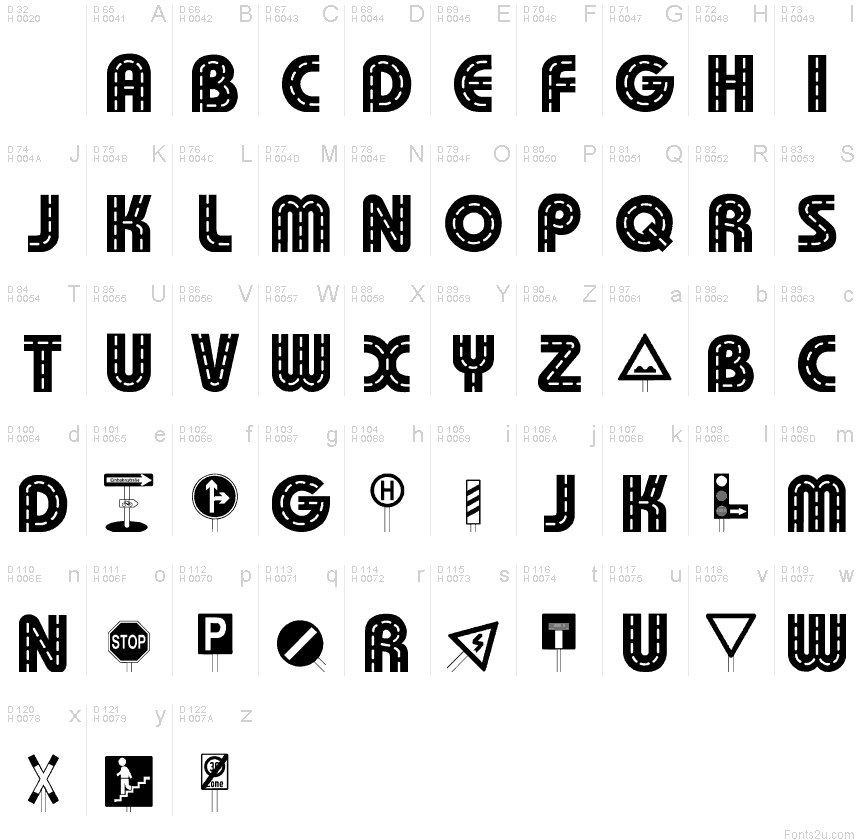
Schilderwald Alt autorstwa Susanne Fiedler to darmowy krój typu display inspirowany oznakowaniem drogowym, o dynamicznym, miejskim charakterze. Litery czerpią z grafiki drogowej i elementów miejskiej infrastruktury – grube czarne kształty, przerywane linie, strzałki, okręgi i pasiaste znaki – dzięki czemu alfabet czyta się bardziej jak zwarty system ikon nawigacyjnych niż zwykły zestaw liter.
Sprawia to, że jest to naturalny wybór do nagłówków plakatów, identyfikacji wizualnych wydarzeń, okładek albumów, plansz tytułowych czy grafik sklepowych, gdzie darmowy font z tak silnym charakterem sygnalizacji szybko nadaje ton. Sprawdza się również w krótkich grafikach muzealnych czy tematycznych wstępach redakcyjnych, zwłaszcza gdy chcesz, aby litery sugerowały ruch, kierunek i miejską nawigację na pierwszy rzut oka.